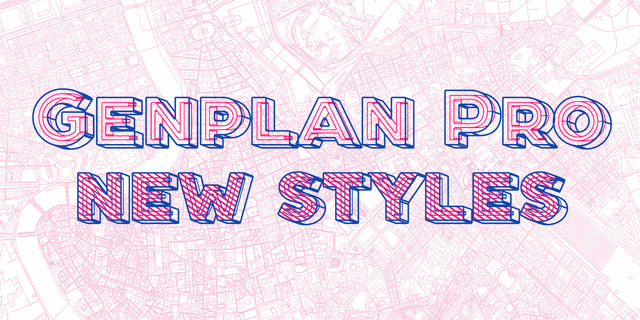
Генплан Про – это акцидентное шрифтовое семейство из девяти типографических слоев с ярким историческим характером. Начертания этого семейства могут использоваться как в спайке, один поверх другого, так и отдельно. Генплан Про основан на рисунке названия генерального плана Москвы 1935 года. Шрифт поддерживает все европейские алфавиты, включая греческий, и все кириллические алфавиты, включая азиатские, содержит знаки верхнего регистра и капитель. Также в набор входят знаки российского рубля, украинской гривны и казахского тенге. Шрифт содержит множество альтернативных глифов, украинские традиционные лигатуры, дискретные лигатуры, языковые альтернативы для польского (черточка), албанского (форма буквы J), и болгарского (треугольные Д и Л). Генплан Про создан для акцидентного использования, а значит отлично подойдет для логотипов, заголовков и буквиц. Шрифт разработан Дмитрием Голубом и выпущен в студии Thundertype в 2014 году.
Функции начертания Genplan Pro Outline
Ассоциации c начертанием Genplan Pro Outline
Качества и характер:
точный ,
ровный ,
твердый ,
железный ,
стальной ,
резкий ,
четкий ,
логичный ,
холодный ,
рабочий ,
промышленный ,
чертежный ,
городской ,
урбанистичный ,
автоматический ,
инженерный ,
статичный ,
устойчивый ,
стабильный ,
технический ,
индустриальный ,
машинный ,
техногенный ,
урбанистический
архитектура ,
архитектор ,
инженер ,
город ,
урбанистика ,
станок ,
завод ,
конструктор ,
игра ,
чертеж ,
робот ,
дизайн ,
техника ,
технологии
Особенности семейства Genplan Pro